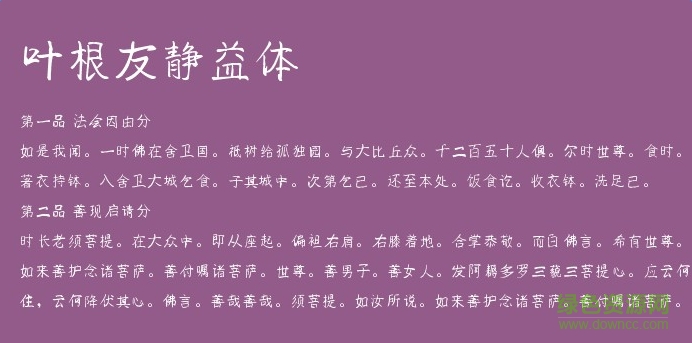
葉根友靜益體字體
葉根友靜益體字體是一款簡約清新風(fēng)格字體軟件,靜益體筆畫工整卻略帶一絲自然,每個字體所在空間一致,創(chuàng)意十足,別有一番韻味,非常受書法家的熱愛與追捧,還有更多好看字體歡迎來綠色資源網(wǎng)下載體驗!
葉根友靜益字體是一款靜益體所謂靜益體就是在字?jǐn)?shù)特別多的情況下 看起來有一種安靜的感覺,不管內(nèi)容多么浮夸都會有一種靜益的感覺,優(yōu)雅自然!
該字體筆畫工整,筆畫的收尾出比較特殊,別有用心的一提,韻味十足,整體效果十分優(yōu)雅安靜,適用于標(biāo)題文章設(shè)計方面,值得使用收藏!